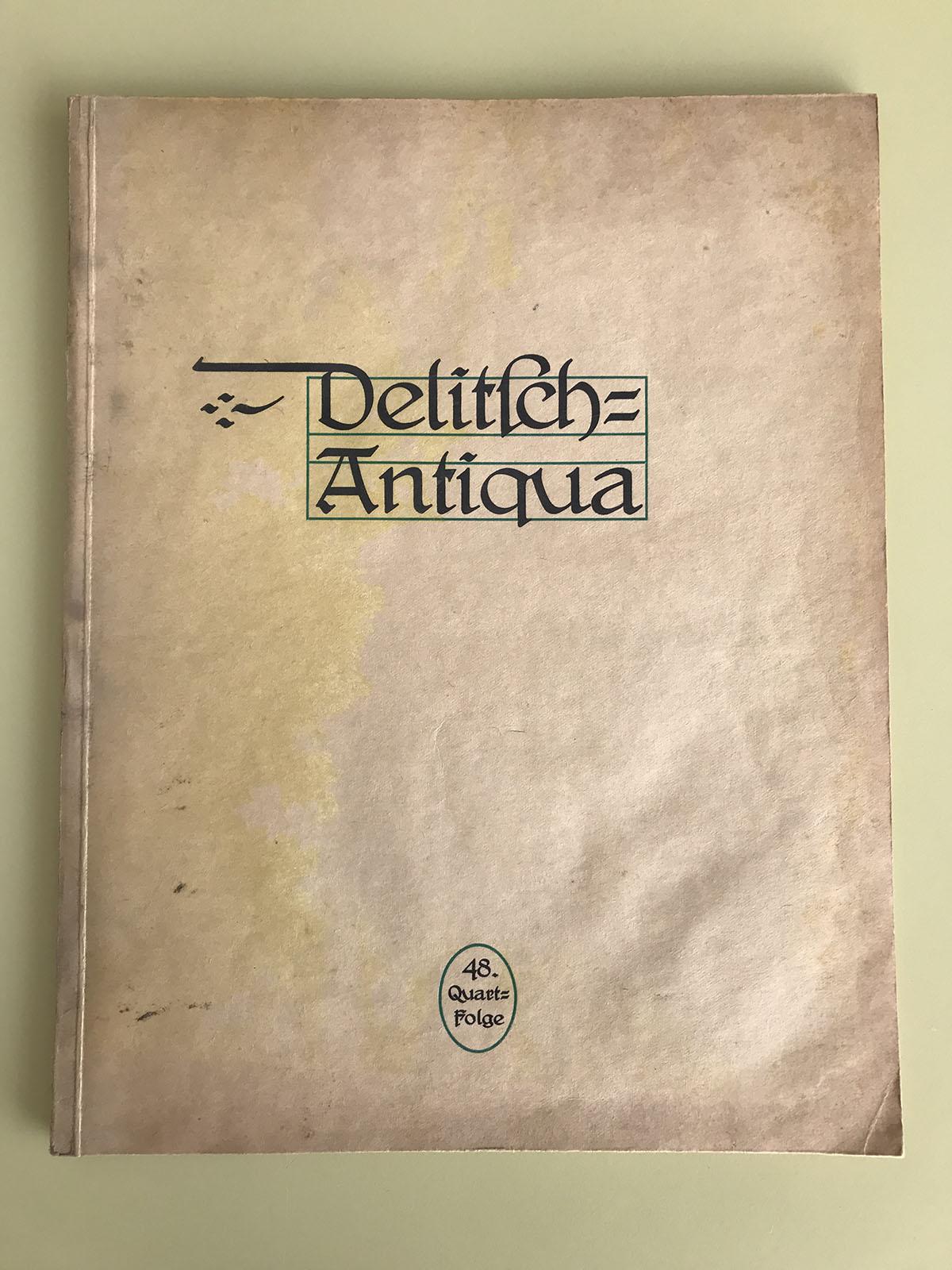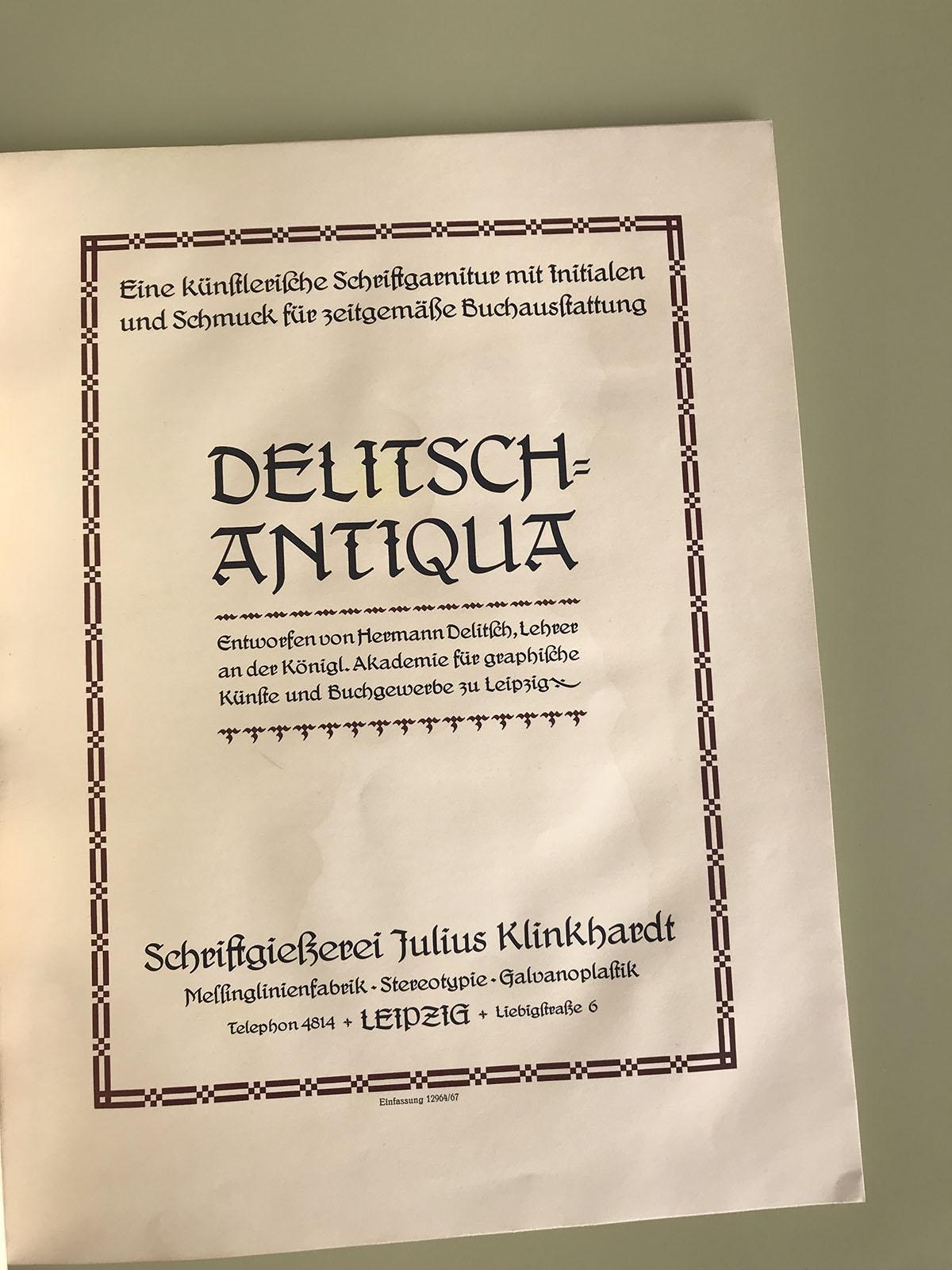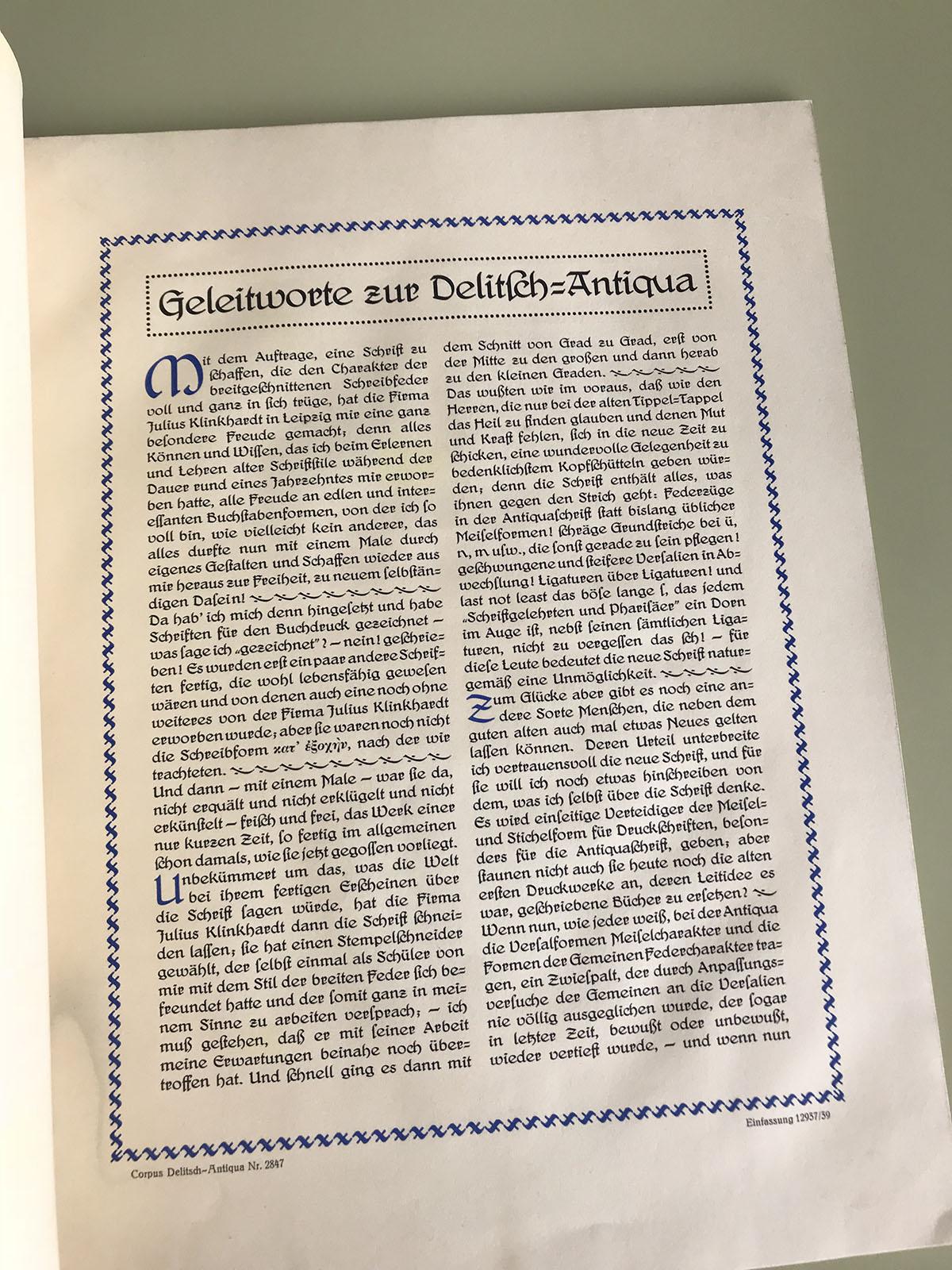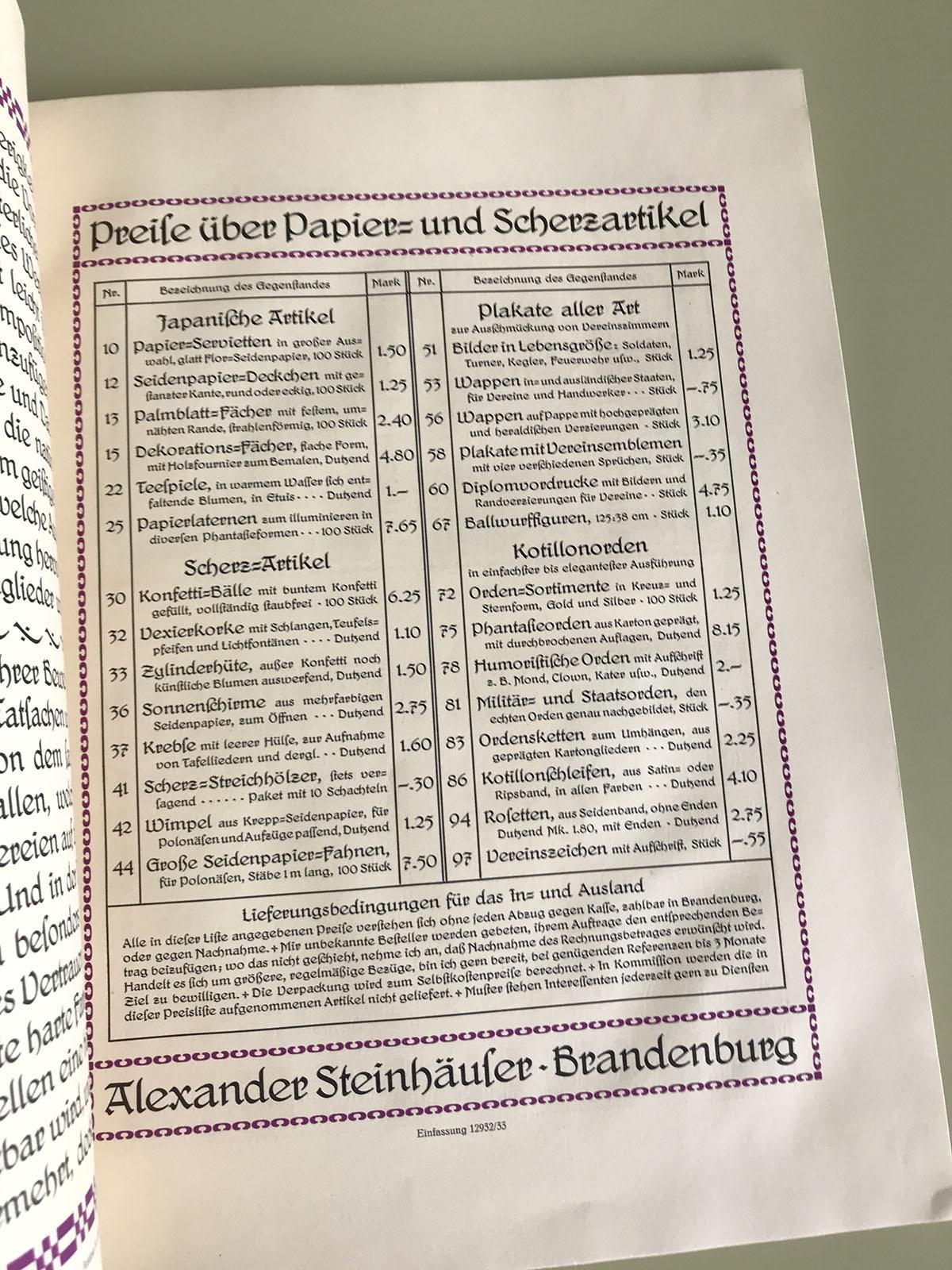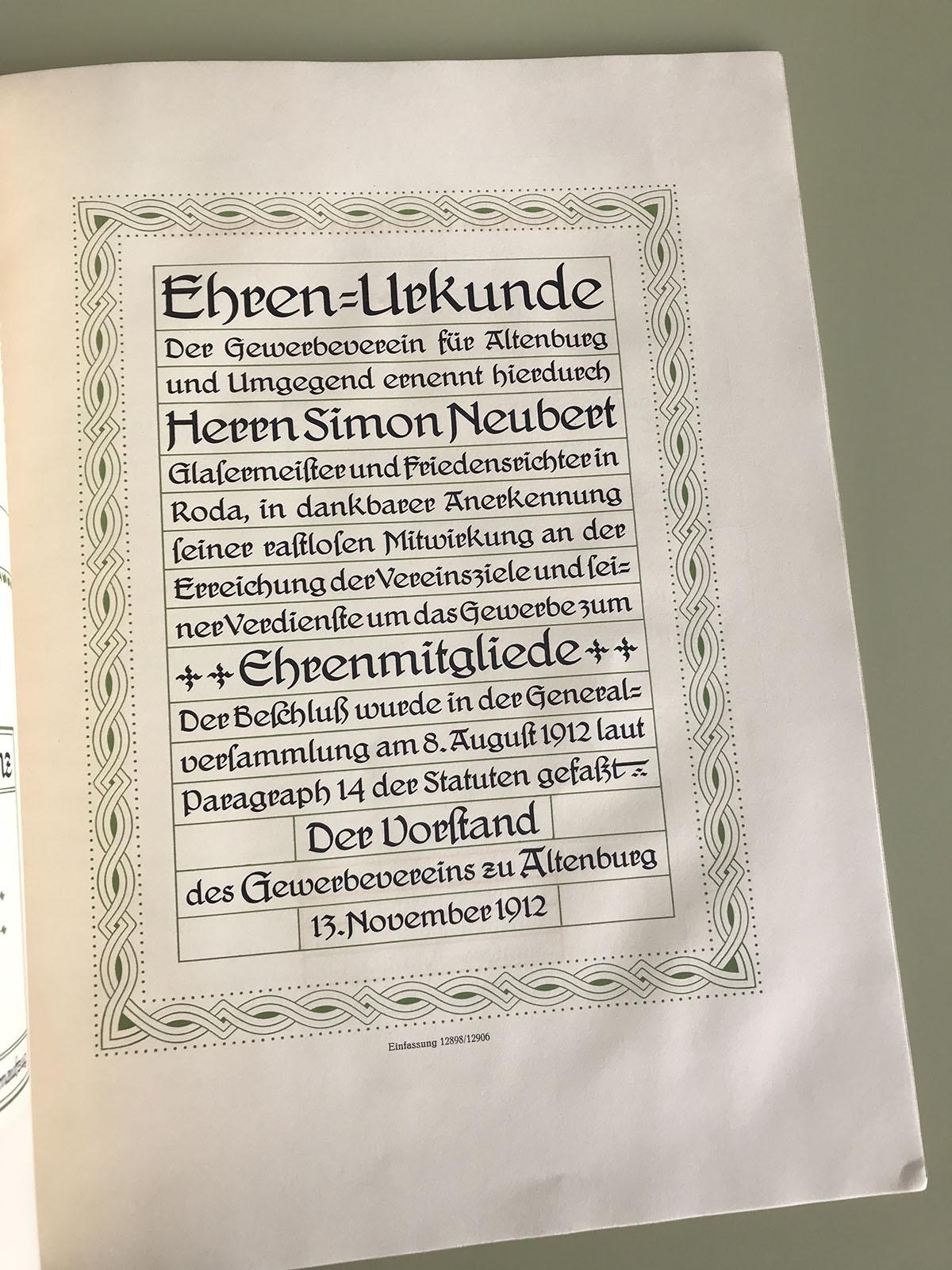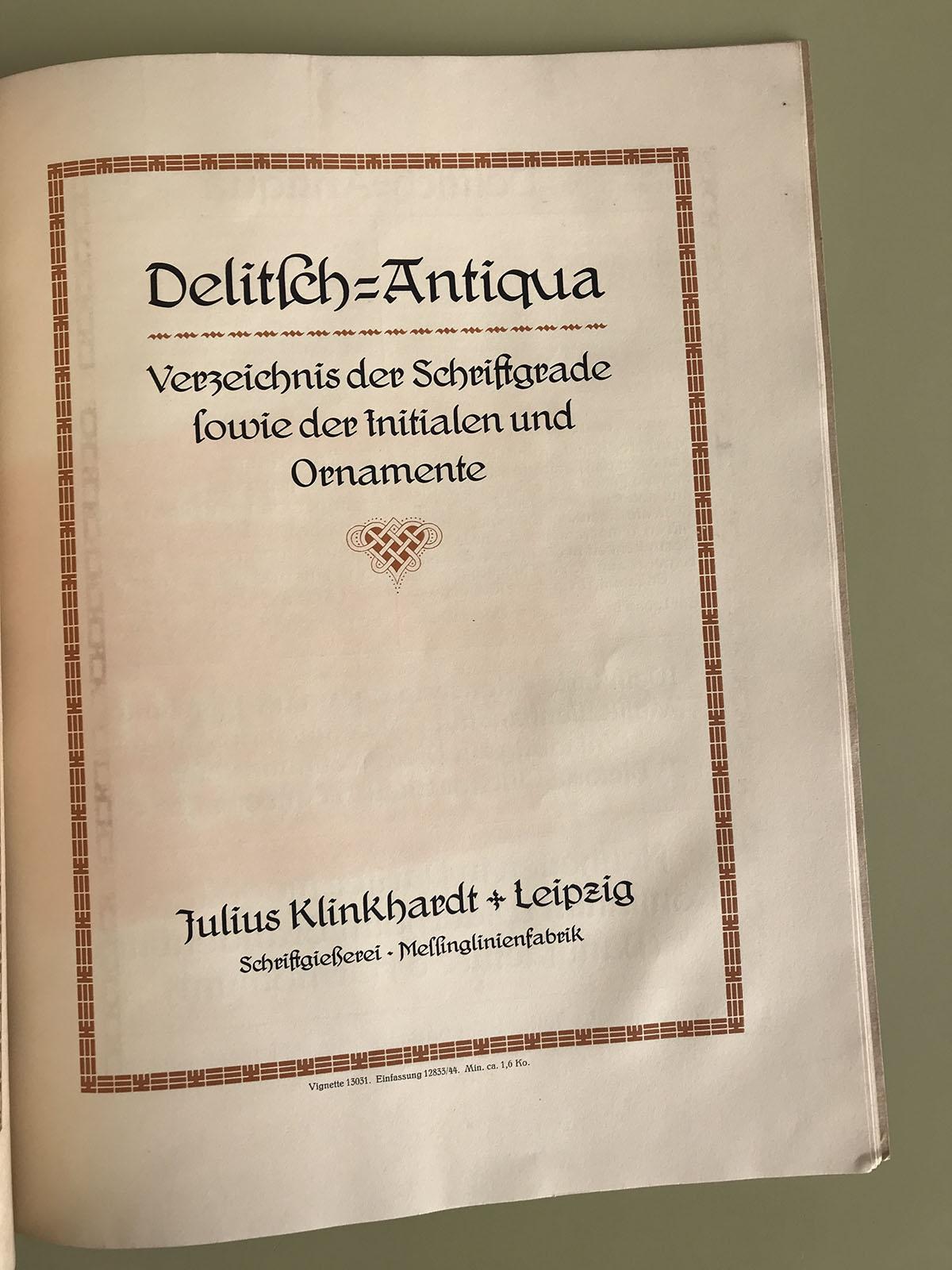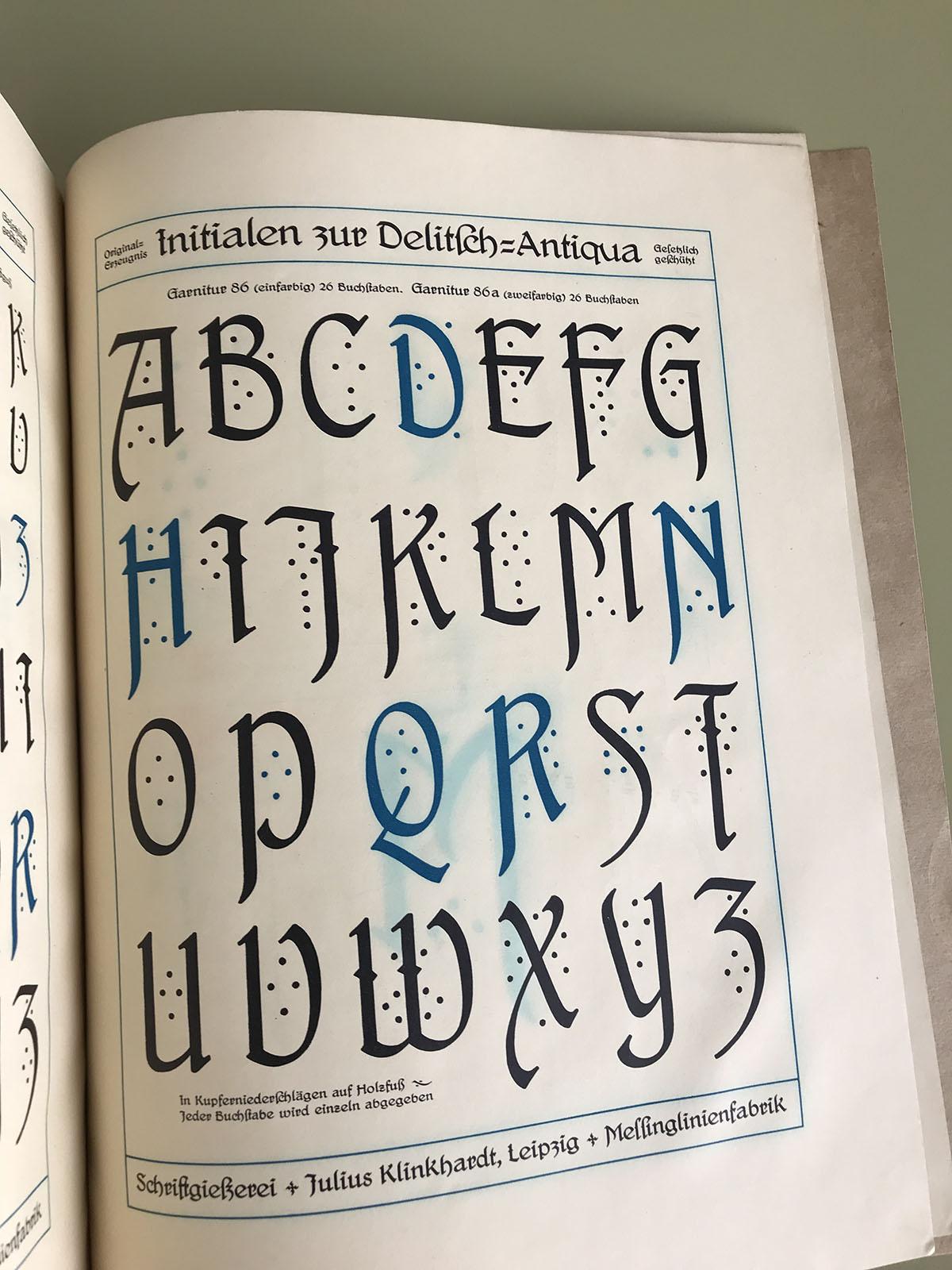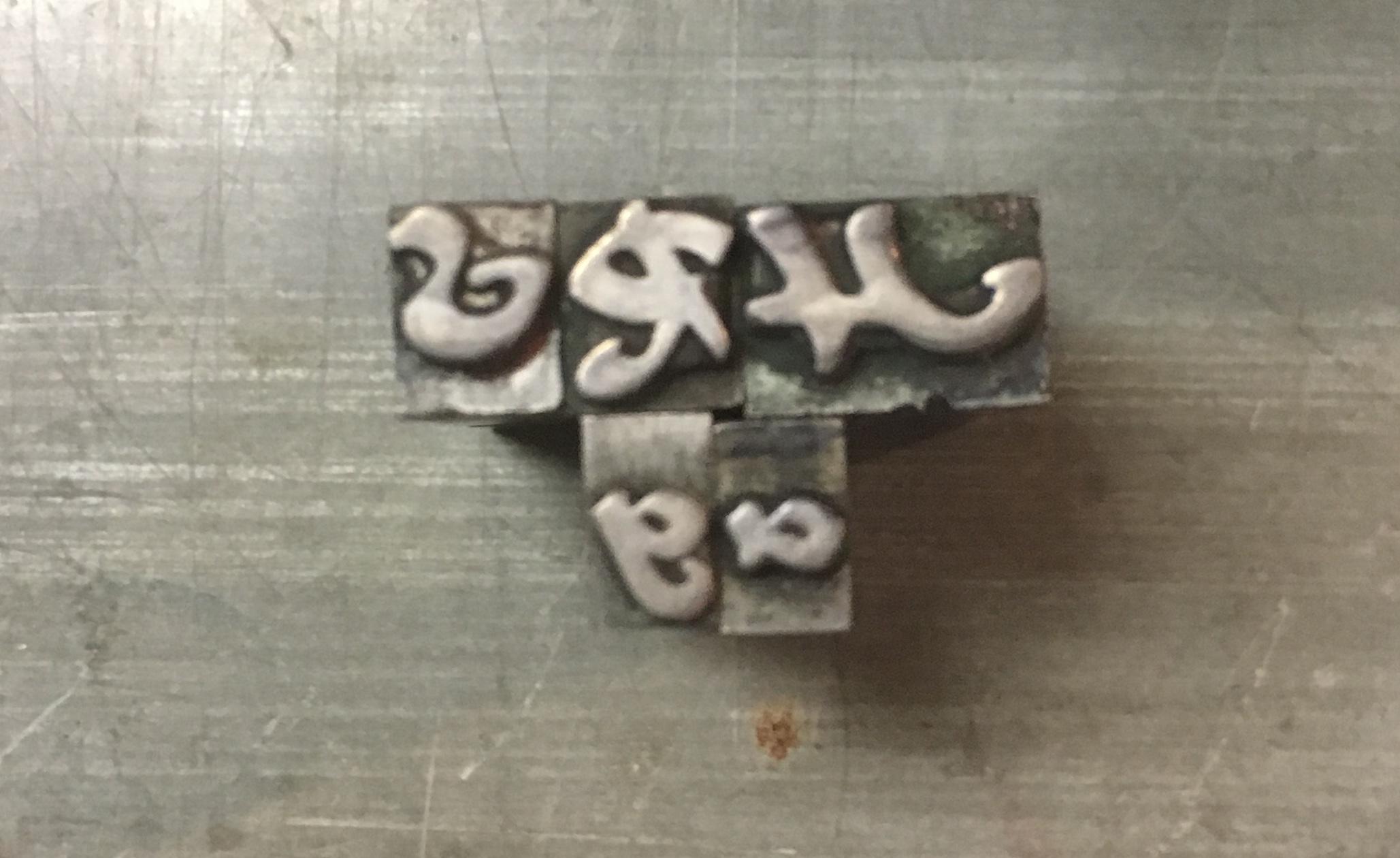
Interessanter Schrank mit vielen namenlosen
Nummer 6 ist heute als "Gans Antigua Manuscrito" erhältlich.
Sie war es zwar nicht, aber es hat mich auf die richtige Spur gebracht. Nämlich durch die Suche von welchen deutschen Foundries Gans Schriften übernommen hat. Die Delitsch-Antiqua ist es: http://www.klingspor-museum.de/KlingsporKuenstler/Schriftdesigner/Delitsch/HDelitsch.pdf
Nummer 4. ist sicher eine der vielen Steinschriften.
Ja, da kann ich mit »Steinschrift« auch leben. Im Seemann ist sie definitiv nicht mit drin.
Bleibt eigentlich nur die Antiqua von Nummer 7, die irgendwie bekannt aussieht und auch eigenständig genug ist. Hier noch einmal neue Bilder:
Und einfach mal ein last not least in seinen Text zu schmuggeln, hat er sich auch getraut. Hätte ich 1911 – in solch einem Text! – echt nicht erwartet. War schon ein selbstbewusster Mensch, der Herr Delitſch.